Apriamo il sipario verso la regina dei procedimenti di stampa, la tipografia, con un po’ di storia e di evoluzione che dal segno mnemonico, fonetico, pittorico, ideografico e alfabetico ha condotto alla stampa tipografica.
Per conservare la memoria delle cose e dei fatti ci si avvaleva della tradizione orale, al racconto ripetuto, di bocca in bocca e di padre in figlio, delle stesse notizie.
Ma per i commerci come per gli archivi dei re questo mezzo non bastava e gli uomini ricorsero prima a segni e sistemi che portarono alla scrittura: solo questa permise di rappresentare o tramandare un fatto, un ordine a distanza di tempo e di luogo. Finiva così la preistoria.
Il periodo mnemonico
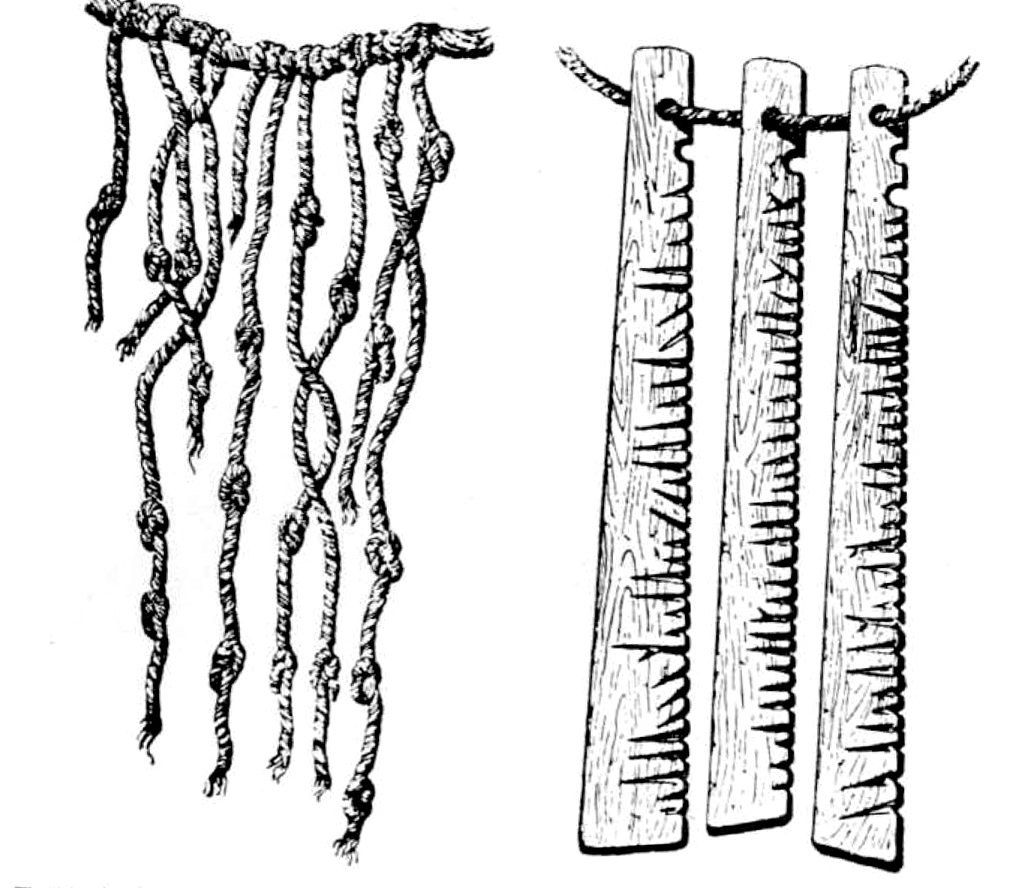
Khipu e stecche di legno intagliate
Sorse l’uso del sistema mnemonico: collocando pietre in forma speciale o cumuli di pietre, detti Galaal, gli uomini tentavano di richiamare alla memoria particolari avvenimenti. Si usarono anche dei cordigli a nodi disposti in modo convenzionale, detti khipu [scritto anche Quipu – ndr] da parte del popolo Inca, un insieme di cordicelle di vario colore annodate, distanziate in modo sistematico tra loro e legate a una corda più grossa e corta a sorreggerle. I khipu erano concepiti per rimanere inalterati. Erano infatti bagnati, fatti seccare e incollati con resine particolari. Scoperti in antichi insediamenti in Perù, servivano per i calcoli matematici. I nodi delle corde erano di diversi colori: rappresentavano numeri, e dalla loro reciproca posizione se ne potevano ricavare le unità, le decine, le centinaia e le migliaia.
Si crede che i khipu fossero utilizzati per calcoli astronomici, fondamentali per la cultura inca, per formule magiche ma anche per descrivere sommariamente avvenimenti storici ed economici. In un suo romanzo Marco F. Picasso dimostra che i khipu fossero un vero sistema di scrittura e non un semplice ‘pallottoliere’ peraltro chiamato Yupana. *
Il periodo pittorico e ideografico
Con la scrittura pittorica − sviluppata in diverse aree del globo − mediante figurazioni a carattere descrittivo, si tramandavano scene di caccia, battaglie, trionfi e altro.
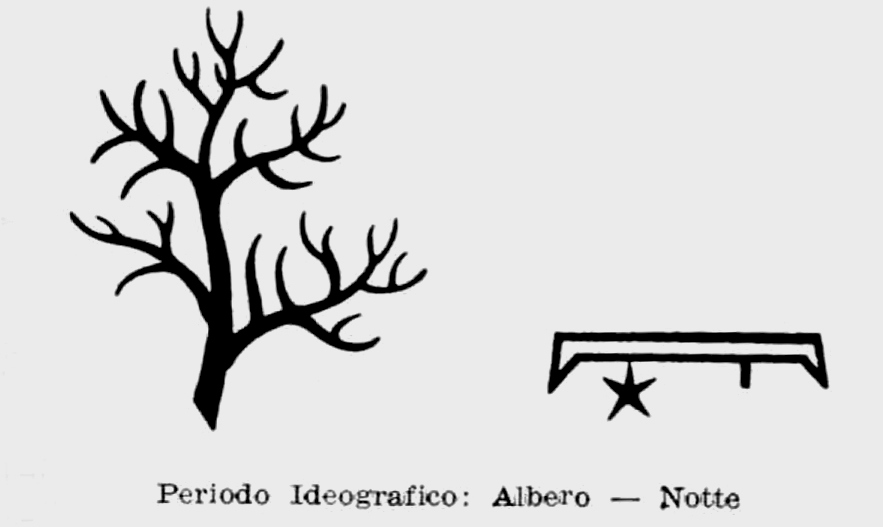
Periodo ideografico- Albero – Notte
Nel tempo per abbreviare questo scomodo, seppur artistico, modo di esprimersi, si passò a una scrittura simbolica che rappresentava già un progresso notevole, una “stenografia”. Furono usati, chi dice dagli egizi, chi dai cinesi, simboli o sigle al posto della raffigurazione estesa.
Questa scrittura, definita ideografica, si suddivise in tre rami:
– geroglifica, per le iscrizioni monumentali e, in seguito, sui papiri (4000 anni a.C.);
– ieratica, usata solo dai sacerdoti, per il culto (3000 anni a.C.);
– demotica, adoperata dal popolo (800 anni a.C.).
Il periodo fonetico
L’ultima trasformazione della scrittura, prima di poterla considerare tale, fu la scrittura fonetica: furono stabiliti segni grafici in corrispondenza della parola che si voleva esprimere. Segni che si suddivisero in verbali, se esprimevano l’intera parola; sillabici, se solo una sillaba; alfabetici, se una sola lettera.
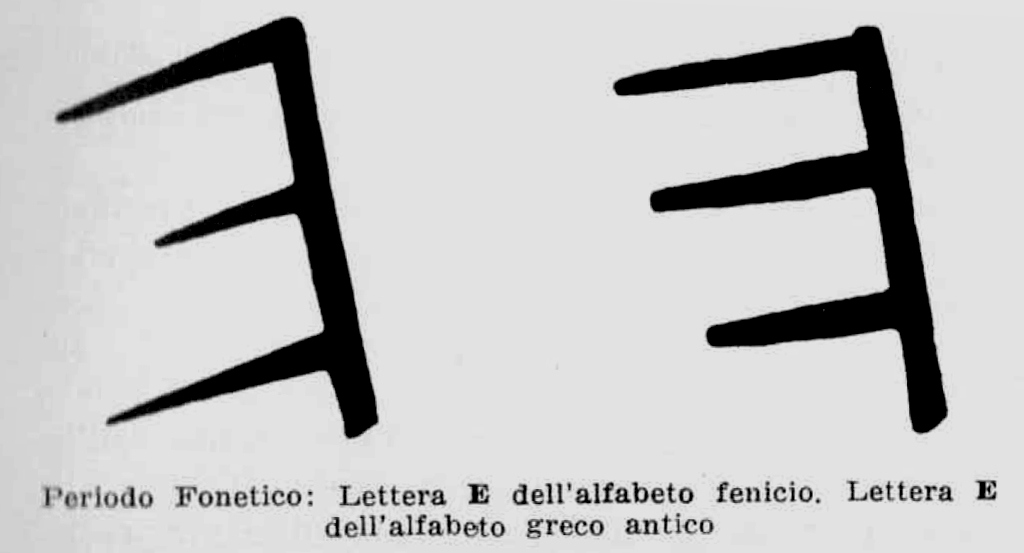
Periodo fonetico. Lettera E alfabeto fenicio e lettera E alfabeto Greco
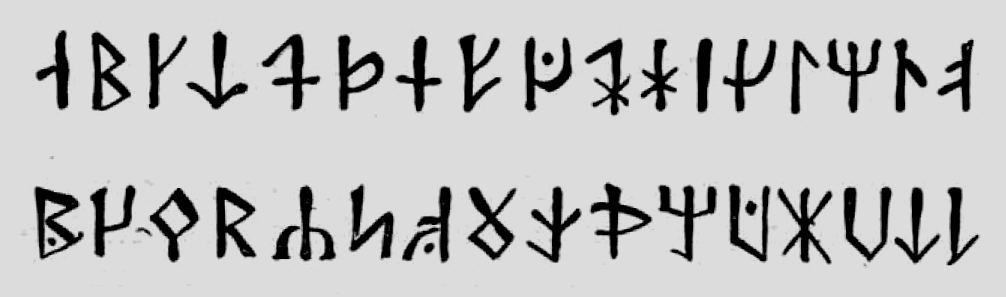
Alfabeto runico
L’alfabeto
Si giunse quindi al vero alfabeto con cui l’umanità poté tramandare in modo completo e durevole, la storia della propria civiltà.
Pare che l’alfabeto da cui ebbe origine quello odierno, sia merito degli antichi popoli che abitavano l’Egitto. I fenici, poi, modificarono il sistema e attribuirono a ogni segno un suono, fondendolo con quello egiziano e ottenendo l’alfabeto parlato e scritto. Questo metodo più facile di espressione del pensiero, passò in Grecia e poi in Italia tra gli Etruschi e quindi dai Romani. Da qui gli infaticabili legionari lo portarono in Germania, dove si fuse con l’alfabeto runico proveniente dalla Scandinavia, creando quello speciale carattere che fu chiamato gotico.
I materiali utilizzati per tracciarvi la scrittura, in ordine cronologico, furono: pietre, pelli di animali, cortecce d’albero, tavolette cerate, e inseguito il papiro, la pergamena e infine e solo molto più tardi, la carta.
Le prime vere scritture erano tracciate sul papiro (circa 2000 anni a.C.), formato da strati sottili e intrecciati della corteccia della pianta di papiro; questo fu poi sostituito dalla pergamena: pelle di capra (o di vitello) opportunamente trattata ed essiccata. Dopo l’anno 1000 della nostra era fu sostituita dalla carta proveniente dai popoli cinesi.
La xilografia
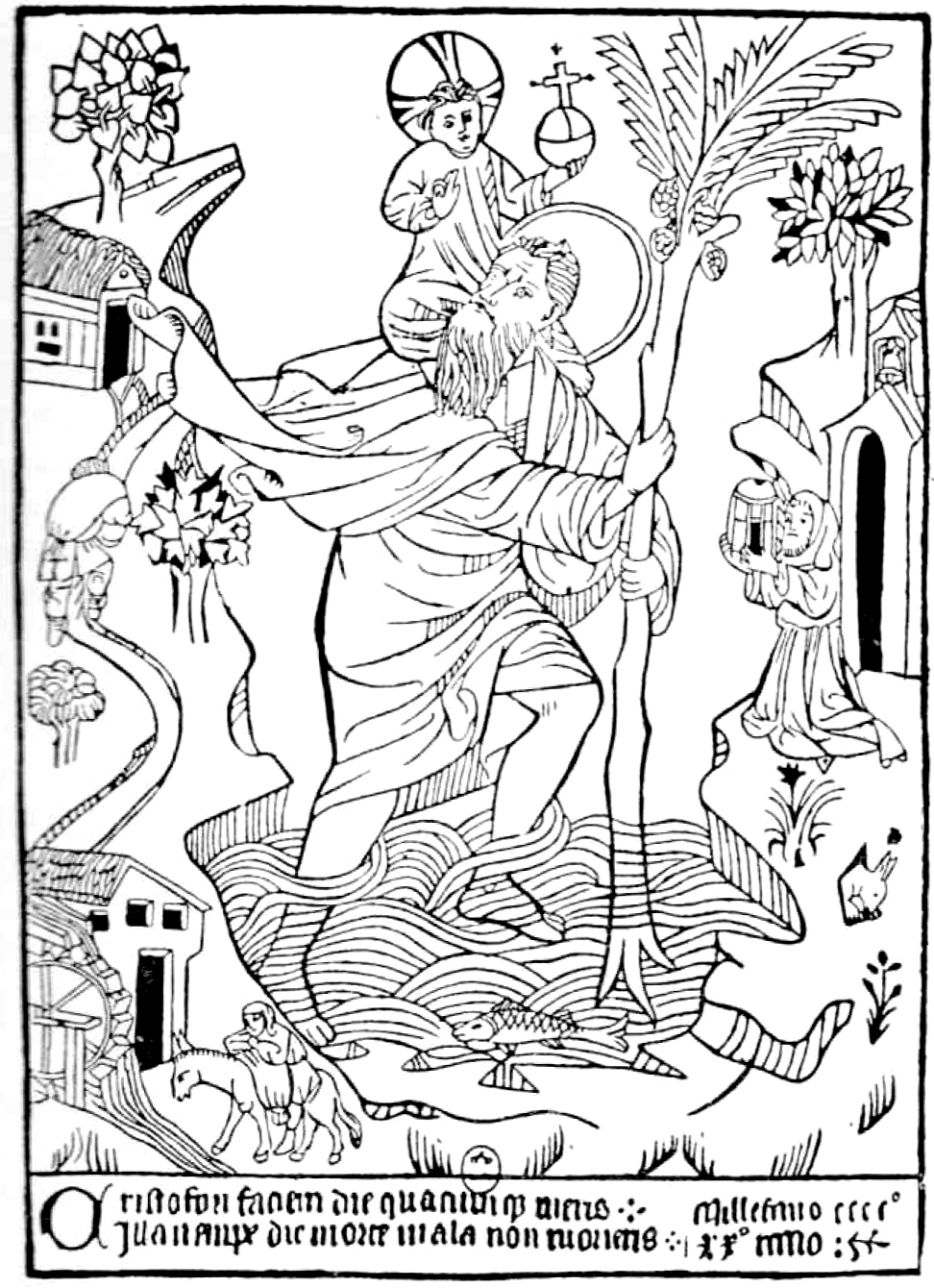
La prima xilografia (1423)
Pure dai cinesi ci pervenne l’arte di incidere sul legno caratteri e disegni (xilografia) e l’invenzione dell’inchiostro, ottenuto trattando il carbone con certe loro speciali resine.
Verso il 1300 esistevano già in Italia carte da gioco e geografiche stampate su carta spessa e con il metodo xilografico. (v. Le origini delle carte da gioco ; Una piccola storia delle carte da gioco).
La prima stampa xilografica con data certa risale al 1423 (Buxheim am Rhein) e rappresenta San Cristoforo con il Bambino Gesù.
La prima fabbrica di carta sorse in Italia a Fabriano tra il 1100 e il 1150. Fino al 1450 e oltre i libri venivano scritti a mano, su pergamena o su carta dagli amanuensi, scrivani di mestiere. I rubricatori colorivano le grandi immagini, i frontoni, i titoli, mentre i miniaturisti abbellivano le pagine dei libri stessi con splendide iniziali.
La stampa a caratteri mobili
Giovanni Gutenberg di Magonza in Germania, i cinesi e soprattutto i coreani prima di lui, inventarono la stampa a caratteri mobili con la quale si poterono replicare i codici manoscritti poiché ogni carattere veniva fuso e forgiato e così poteva essere riutilizzato per innumerevoli composizioni a stampa. L’arte della stampa, verso il 1454, sconvolse le abitudini e i sistemi di quel tempo e permise la diffusione della scienza e della religione. Infatti il primo libro a stampa fu la Bibbia delle 42 righe di Gutenberg.
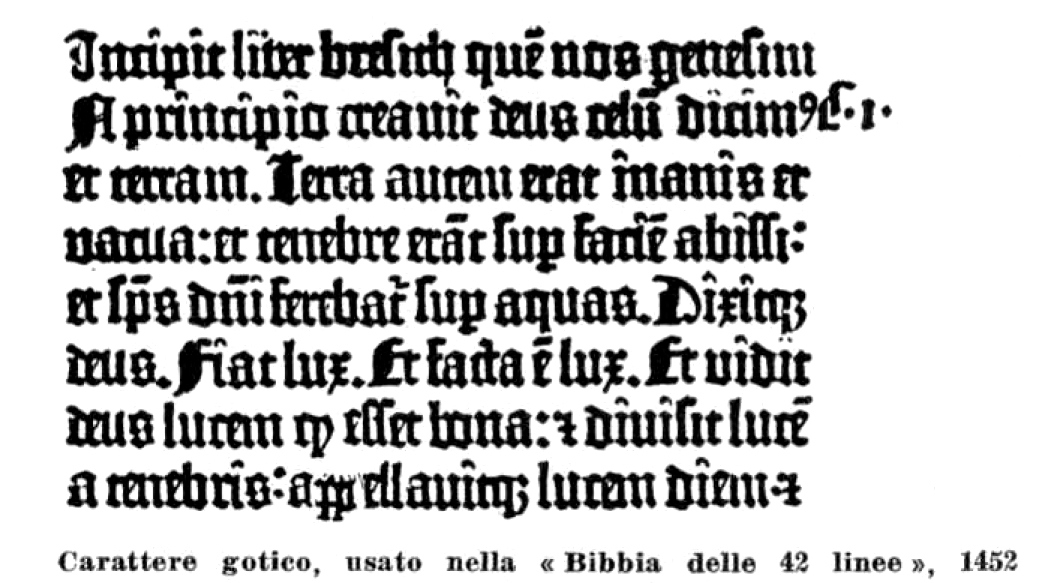
Carattere gotico usato nella Bibbia delle 42 righe
Questa arte intorno al 1500 si era divulgata così rapidamente da giungere in Italia, prima a Subiaco poi a Venezia nel 1469 per poi diffondersi in altre città della penisola. Si trattava dei primi libri, detti incunaboli (per convenzione solo quelli fino al 1499), ovvero libri nella culla.
L’Italia vanta celebri tipografi, tra i quali: Panfilo Castaldi, Aldo Manuzio inventore del ‘libro tascabile’ che conosciamo oggi, la cui attività fu proseguita dal figlio e oltre, dei Giunta, dei Giolito sino a raggiungere il sommo Giambattista Bodoni vissuto a Parma tra il 1740 e il 1813. Bodoni fu il rinnovatore della nostra arte tipografica, conferendole quella dignità e valore artistico giunti fino a noi nei suoi meravigliosi libri, punzoni e nel suo splendido alfabeto e nelle sue rilegature.
Grandi figure di tipografi esteri furono le casate degli Estienne e dei Didot e il Garamond in Francia, Elzevier in Olanda, Baskerville in Inghilterra, il Plantin in Belgio (ad Anversa che ospita oggi uno dei più bei Musei della Stampa), Ibarra in Spagna.